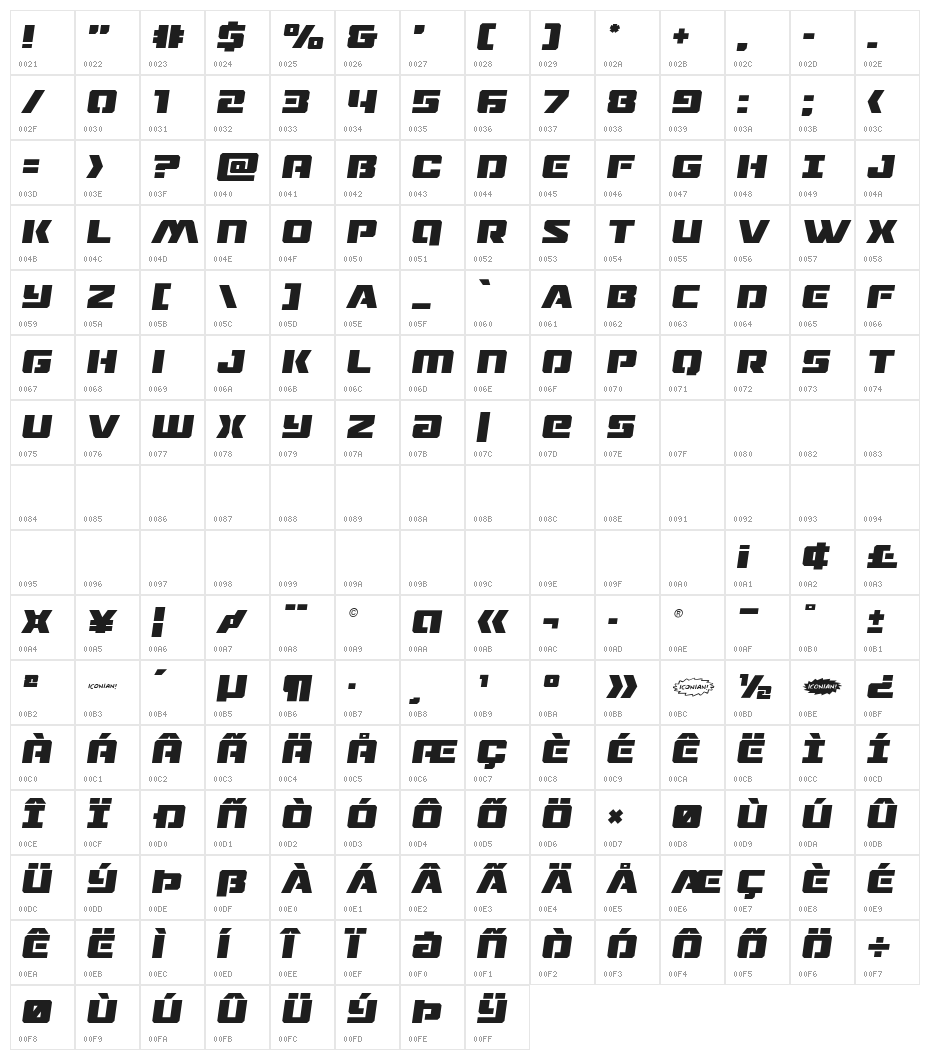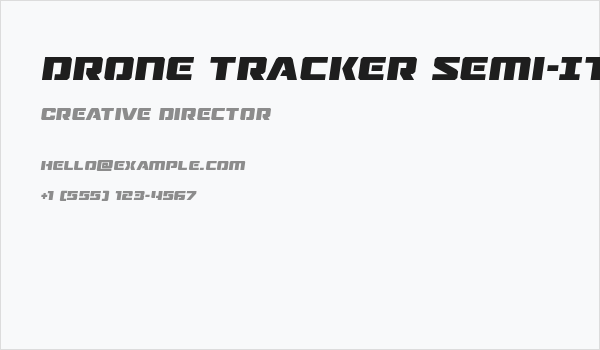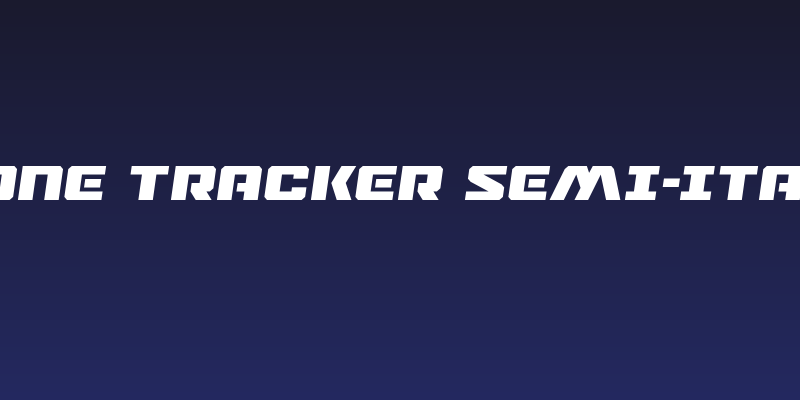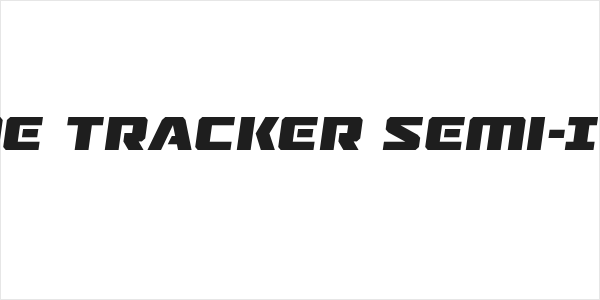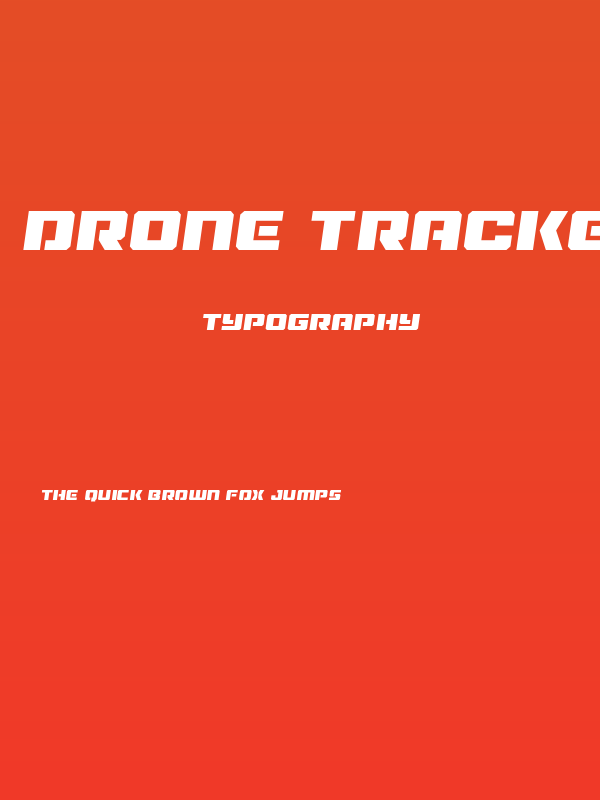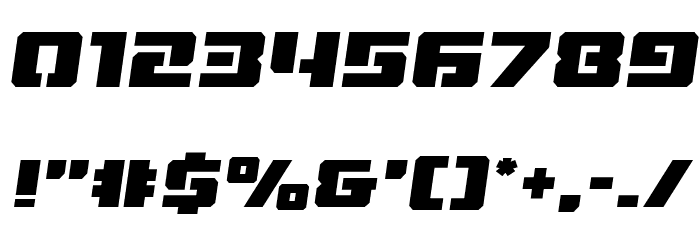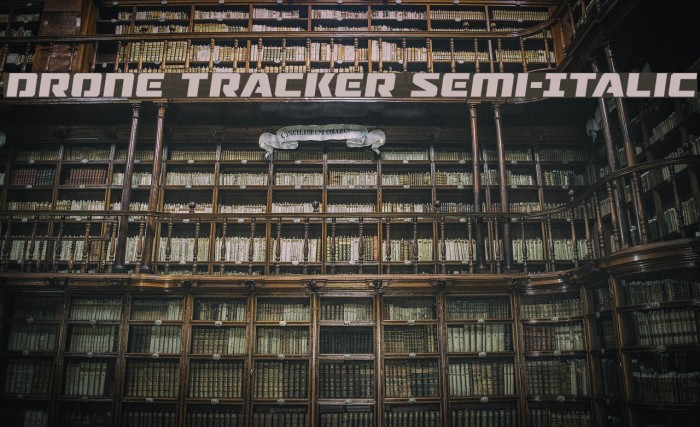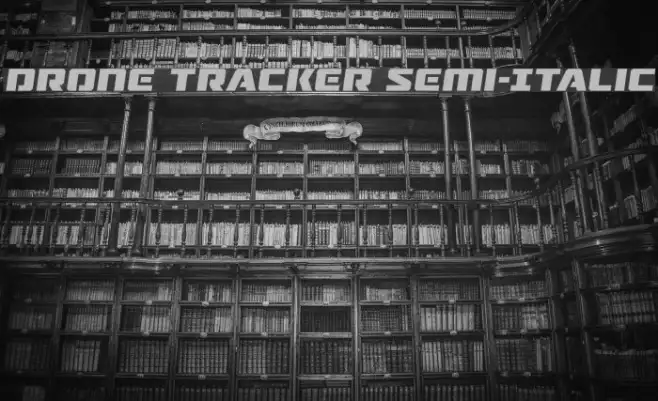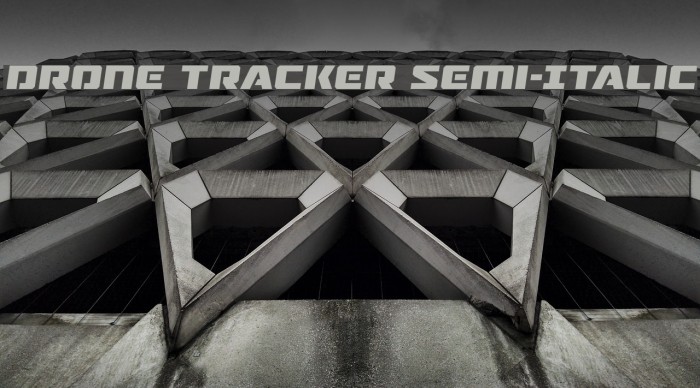
Drone Tracker Semi-Italic Font
| Proyectos propuestos | Ideal for technology branding, video game titles, sci-fi movie posters, and sports team logos. |